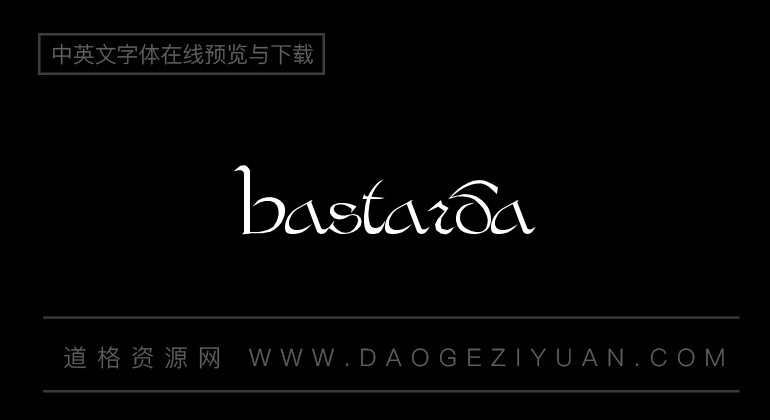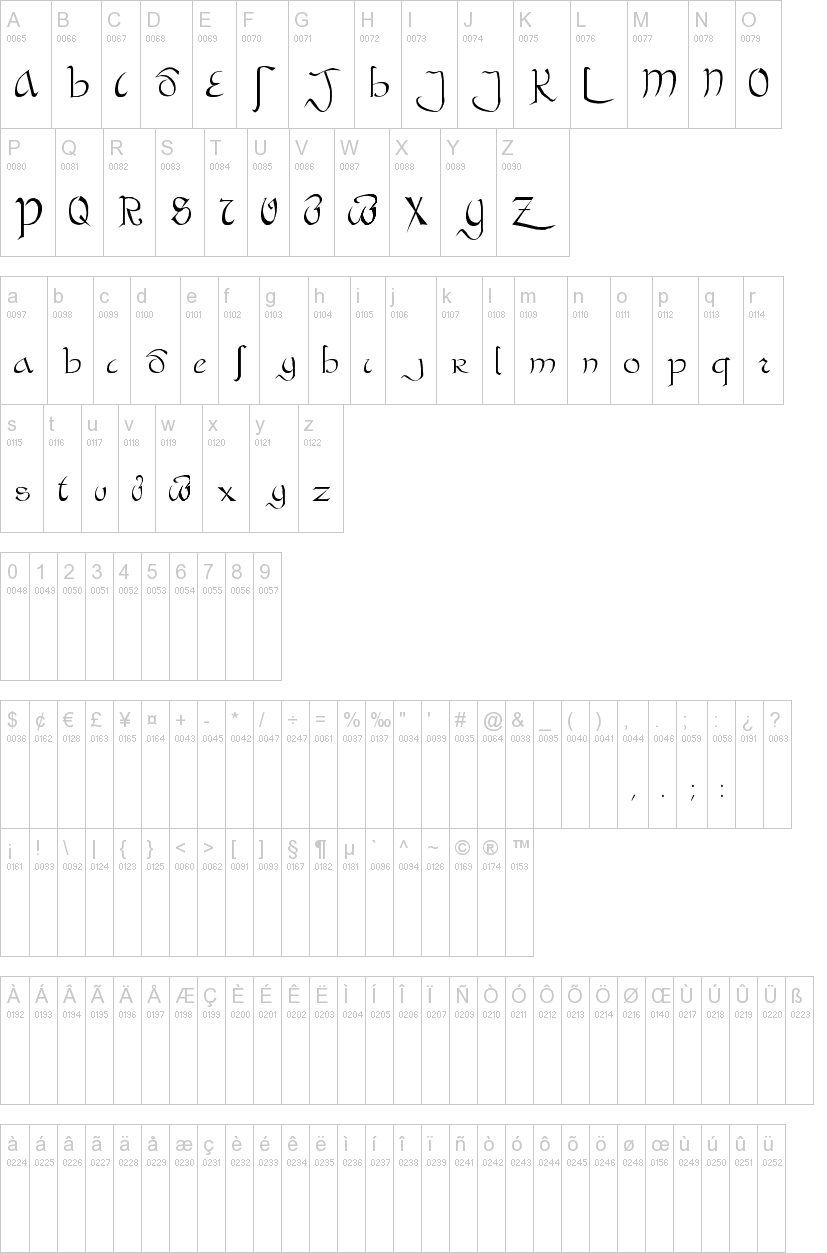
Bastarda 字体是一种罗马手书字体,它被认为是一种古老的手写字体,可以追溯到15世纪欧洲。它的字体特征是由粗细混合的笔画组成,字体粗细不均匀,笔画粗细不同,且具有鲜明的对比度,整体格式较为粗犷,具有独特的风格。Bastarda 字体通常用于古代卷轴、古典书籍、古老的报纸、绘画和绘画等。内容介绍
Bastarda是一款非常不错的手写艺术字体,具有很好的视觉感,适合于文化类的宣传设计、商业类品牌的广告和产品包装设计以及个性化文字排版等较多场景。